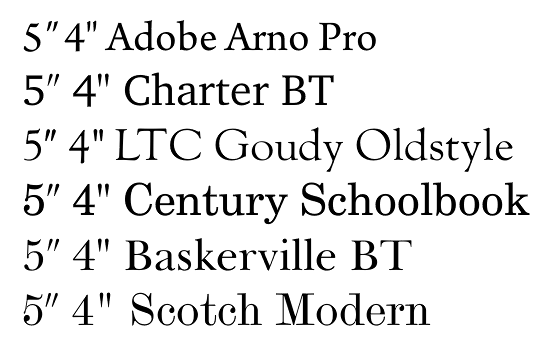
Richtung der Guillemets
Seit wann ist ein Zoll-/Minutenzeichen ein Anführungszeichen?
Dieses Zeichen: " ist kein Zoll-/Minutenzeichen, sondern ein Ersatzzeichen, das als Anführungs-, Zoll- und Sekundenzeichen benützt werden kann. Es als Anführungszeichen zu benützen ist also genauso richtig wie es als Zoll- oder Sekundenzeichen zu verwenden.
Das typographische Zeichen für Zoll/Sekunden liegt auf der Unicode-Stelle 2033. Beispiel:
15?
Seit wann ist ein Zoll-/Minutenzeichen ein Anführungszeichen?
Dieses Zeichen: " ist kein Zoll-/Minutenzeichen, sondern ein Ersatzzeichen, das als Anführungs-, Zoll- und Sekundenzeichen benützt werden kann. Es als Anführungszeichen zu benützen ist also genauso richtig wie es als Zoll- oder Sekundenzeichen zu verwenden.
Ja, ich weiß, dass eigentlich ? das Minuten-/Zollzeichen ist, ich habe hier nur die (leider) gebräuchliche Ersetzung mit dem Namen des Originals benannt.
Ich würde sagen, es funktioniert in allen Programmen, die direkt Apples Text Engine verwenden. Firefox, Word und alle Adobe-Programme fallen somit leider raus. Denke aber mal, es wird prinzipiell auch in nicht-Apple-Programmen funktionieren.
Dieses Zeichen: " ist kein Zoll-/Minutenzeichen, sondern ein Ersatzzeichen, das als Anführungs-, Zoll- und Sekundenzeichen benützt werden kann.
Das typographische Zeichen für Zoll/Sekunden liegt auf der Unicode-Stelle 2033. Beispiel:
15?
Da würde ich widersprechen wollen. Das vermeintlich »richtige« Zollzeichen ist in keiner Satzschrift enthalten und ist mir in meinem Leben noch nicht ein einziges Mal im Druck oder anderswo begegnet. Millionen von Bildschirm-Verpackungen tragen das Doublequote-Zeichen und jeder Leser kennt nur dieses – ergo: DAS ist das Zollzeichen.
Zu sagen, es wäre falsch, ist so, wie ein beliebiges deutsches Wort im etymologischen Wörterbuch nachzuschlagen und dann zu fordern, die allgemein anerkannte Bedeutung wäre jetzt plötzlich falsch, da das Wort irgendwann mal eine andere Bedeutung hatte. Aber nach diesem Ansatz könnte man keinen deutschen Satz mehr sagen, weil einen niemand mehr versteht. Es kommt darauf an, welche allgemein anerkannte Bezeichnung wie den Wörtern und Zeichen heute(!) geben.
Ralf: Da Du den Doppelstrich selbst auch als Anführungszeichen benützt, mußt Du wohl zugeben, daß es sich Deiner Meinung nach nicht nur um ein Zeichen für Zoll, sondern auch für Anführungen handelt. Und ich habe nichts anderes behauptet!
Es als Anführungszeichen zu benützen ist also genauso richtig wie es als Zoll- oder Sekundenzeichen zu verwenden.
Ich bin also sehr wohl der Meinung, daß es richtig ist, den Doppelstrich als Zollzeichen zu benützen, genauso als Anführungs- und Sekundenzeichen. Genau dafür wurde das Zeichen ja geschaffen: Als ein Ersatzzeichen, das man für all diese Fälle gebrauchen kann.
Genauso wie es jedoch auch die eigentlichen Anführungszeichen weiter gibt, gibt’s auch das eigentliche Zollzeichen weiter.
Daß es nur wenige benützen, ist ja wohl kein Wunder: Nur wenige wissen vermutlich, daß es dieses Zeichen überhaupt gibt, und ebenfalls wenige würden sich die Mühe machen, es irgendwie rauszusuchen. Das ändert doch aber nichts an der Bedeutung des Zeichens, oder daran, daß es das Zeichen überhaupt gibt. Genauso wie beispielsweise das große Eszett nur von wenigen benützt wird. Trotzdem gibt’s das, und es ist richtig! In wissenschaftlichen Zeitschriften und Büchern ist das eigentliche Zoll-/Sekundenzeichen allerdings durchaus üblich.
Daß das Zollzeichen in keiner Satzschrift enthalten ist, ist falsch. Es stimmt aber, daß es in nur wenigen Schriften enthalten ist. Das ist ärgerlich, gerade da es so ein einfaches und leicht herzustellendes Zeichen ist. Aber es ist ja auch nichts neues: Sonderzeichen waren früher in noch viel weniger Schriften enthalten als heute. Und an der Bedeutung des Zeichens ändert das ja wohl auch nichts!
Immerhin enthält die Windows Glyph List 4 das Zeichen, es ist also in den Systemschriften Times, Georgia und Verdana enthalten, genauso in der Palatino. Ein paar weitere Beispiele (jeweils mit dem Ersatzzeichen zum Vergleich):
Nur wenige wissen vermutlich, daß es dieses Zeichen überhaupt gibt, und ebenfalls wenige würden sich die Mühe machen, es irgendwie rauszusuchen. Das ändert doch aber nichts an der Bedeutung des Zeichens, oder daran, daß es das Zeichen überhaupt gibt.
dass es existiert, heißt aber doch nicht, dass es gebräuchlich und verständlich ist. irgendeinen punkt muss es ja geben, an dem man sagen kann: die meisten leute, selbst die meisten fachleute, wissen nicht, ob und wie man ein bestimmtes zeichen verwenden soll, kennen es vielleicht gar nicht. bei anführungszeichen ist fast jedem bewusst, dass es verschiedene formen gibt, die man vielleicht nicht alle selbst benutzt, aber die man auch ohne kontext erkennen kann (aktiver vs. passiver zeichenvorrat). das gilt für das zollzeichen nicht (mehr).
Als Spezialität zeige ich hier noch »Guillemets« aus der Bodoni und der Didot:
Anf%C3%BChrung3.PNG (gesetzt aus der Bodoni Old Face Pro) Anf%C3%BChrung4.PNG (gesetzt aus der Didot LT Std)
Da bin ich dann froh, dass wir die »Guillemets« nach innen zeigen lassen. Andernfalls käme es mir immer so vor, als würde ich das Zitat in Klammern setzen.